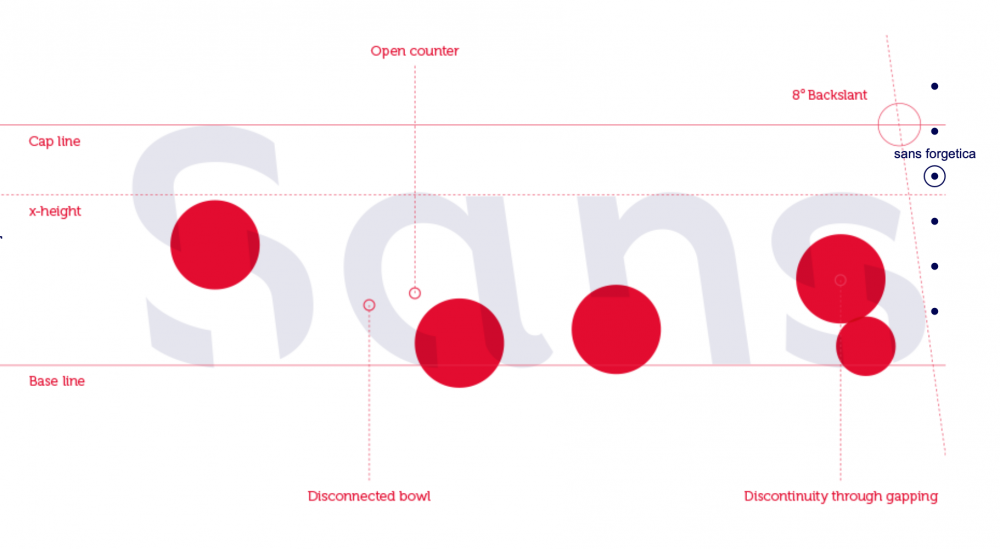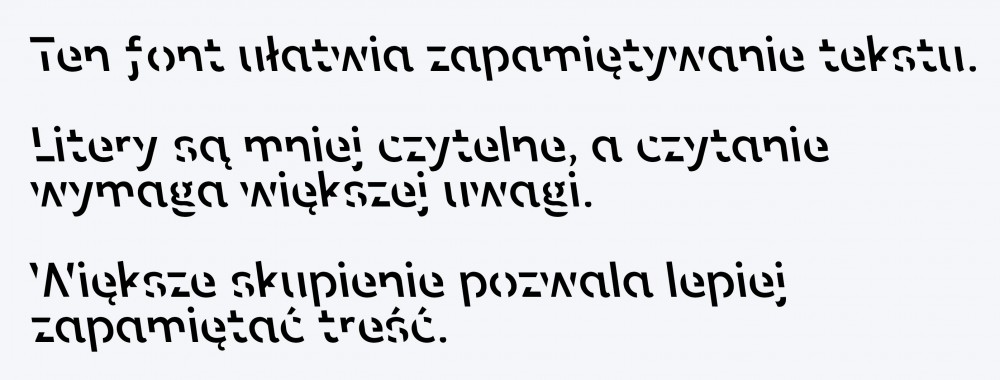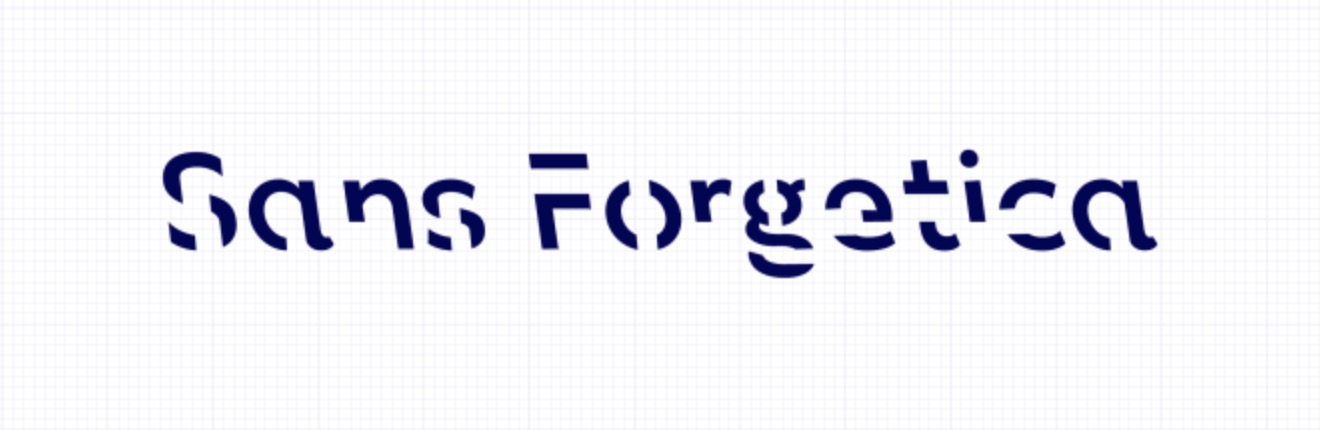
Sans Forgetica wygląda jakby ktoś wymazał części liter
Sans Forgetica to nowy font, który powstał w jednym celu: ma ułatwiać zapamiętywanie czytanego tekstu. Czy faktycznie działa? Możesz to sprawdzić na sobie, bo font jest dostępny za darmo.
Naukowcy stworzyli font, dzięki któremu zapamiętasz więcej
Wbrew pozorom w dzisiejszym świecie czytamy więcej niż kiedykolwiek. Czytamy w pracy, w domu, w czasie wolnym, a nawet w kolejce w sklepie. To fakt, spadki czytelnictwa książek nie biorą się znikąd, bo dziś czytamy głównie krótkie treści na smartfonie. Niemniej jednak: czytamy.
Nagłówków, wpisów i artykułów widzimy dziennie tak wiele, że o większości zapominamy szybko po przeczytaniu. Powstał font, który ma to zmienić.
Font Sans Forgetica wygląda dziwnie, ale ma być skuteczny.
Sans Forgetica to nowy font stworzony przez naukowców z australijskiej uczelni wyższej RMIT. Jego twórcy przekonują, że treści w Sans Forgetica są lepiej zapamiętywane przez nasze mózgi. Wygląd fontu możecie zobaczyć poniżej.
Jak to działa? Font został zaprojektowany w taki sposób, żeby jego odczytanie było trudniejsze niż klasycznego tekstu. W tym celu litery są nachylone w lewo, a więc w innym kierunku niż w klasycznej kursywie, a ponadto linie są przerywane. Całość wygląda tak, jakby fragmenty tekstu zostały źle wyświetlone.
To wszystko sprawia, że font wymaga większej uwagi przy czytaniu. Większe skupienie ma się przełożyć na lepsze zapamiętanie treści.
Zamysł jest słuszny.
Po chwili obcowania z fontem trudno ocenić jego skuteczność, ale sam zamysł jest bardzo słuszny. Z rozmów z nauczycielami i pracownikami uczelni można wywnioskować, że młodzi ludzie zapamiętują mniej. Taki sam wniosek znajdziemy w wielu badaniach.
Powszechny dostęp do internetu sprawia, że nasze mózgi trochę się rozleniwiły. Bardzo często zamiast zapamietać informację, zapamiętujemy miejsce, w którym ta informacja się znajdowała. Na studiach dokładnie pamiętamy, w którym miejscu w książce była informacja, ale nie pamiętamy jej treści. Podobnie w codziennym życiu: pamiętamy kto i gdzie wrzucił dany post w mediach społecznościowych, ale o treści zapominamy.
Podświadomie czujemy, że nie trzeba zaprzątać sobie głowy informacjami, bo w przyszłości możemy po nie sięgnąć ponownie.
Jeśli jesteś studentem i tworzysz dużo cyfrowych notatek, warto dać szansę nowemu fontowi. W najgorszym wypadku nie da to żadnych korzyści, a jeśli twórcy mają rację, być może zapamiętywanie notatek będzie skuteczniejsze.